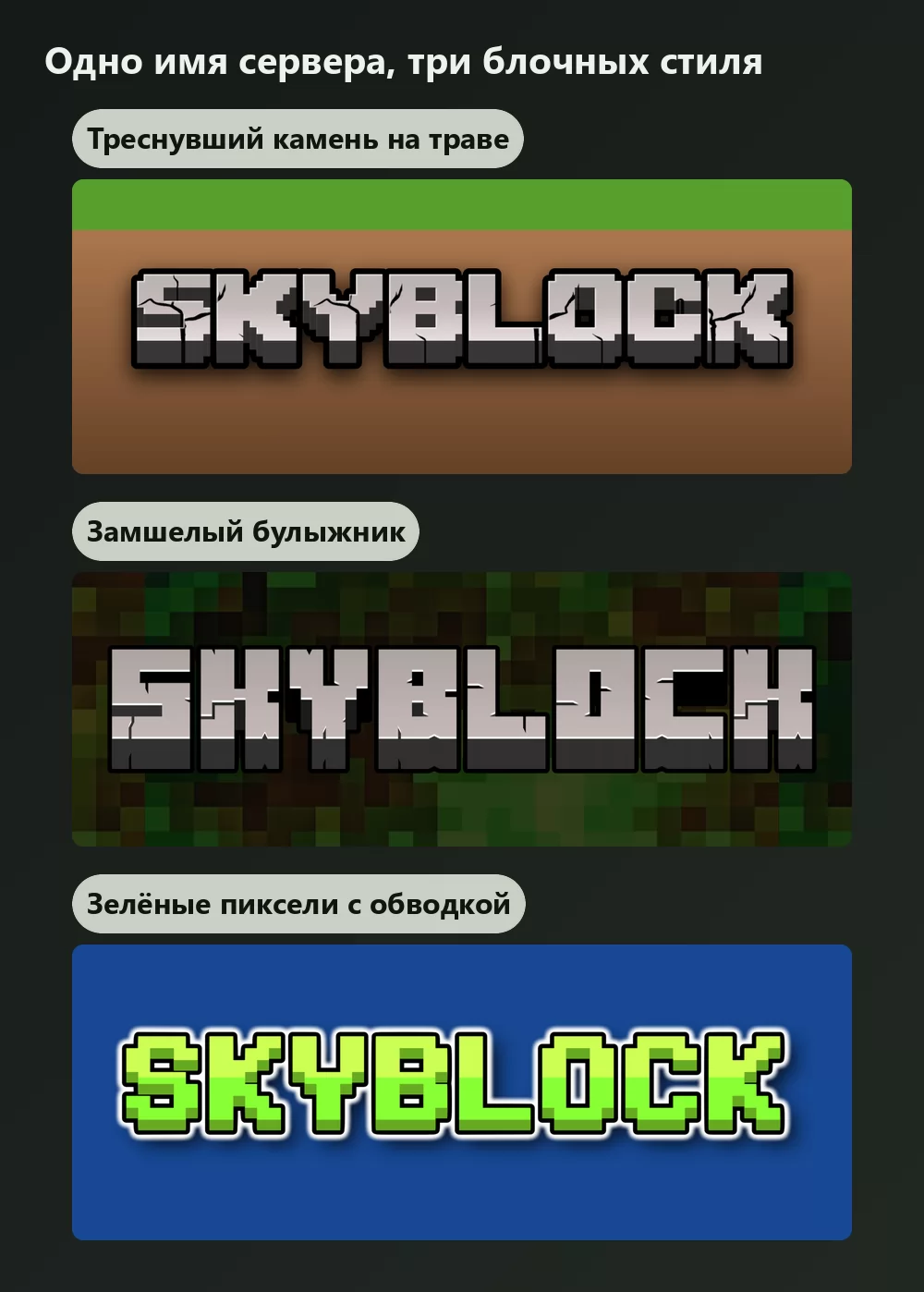
Наберите «шрифт Minecraft» в поисковике, и вы получите две группы результатов, которые противоречат друг другу. Одна предлагает плоский пиксельный шрифт. Другая предлагает толстые каменные буквы с трещинами. И те и другие называют себя шрифтом Minecraft.
Правы обе, потому что Minecraft использует два совершенно разных шрифта, а игра поставляет только один из них. Почти все, кто ищет, представляют себе второй.
Короткий ответ: это два шрифта, а не один
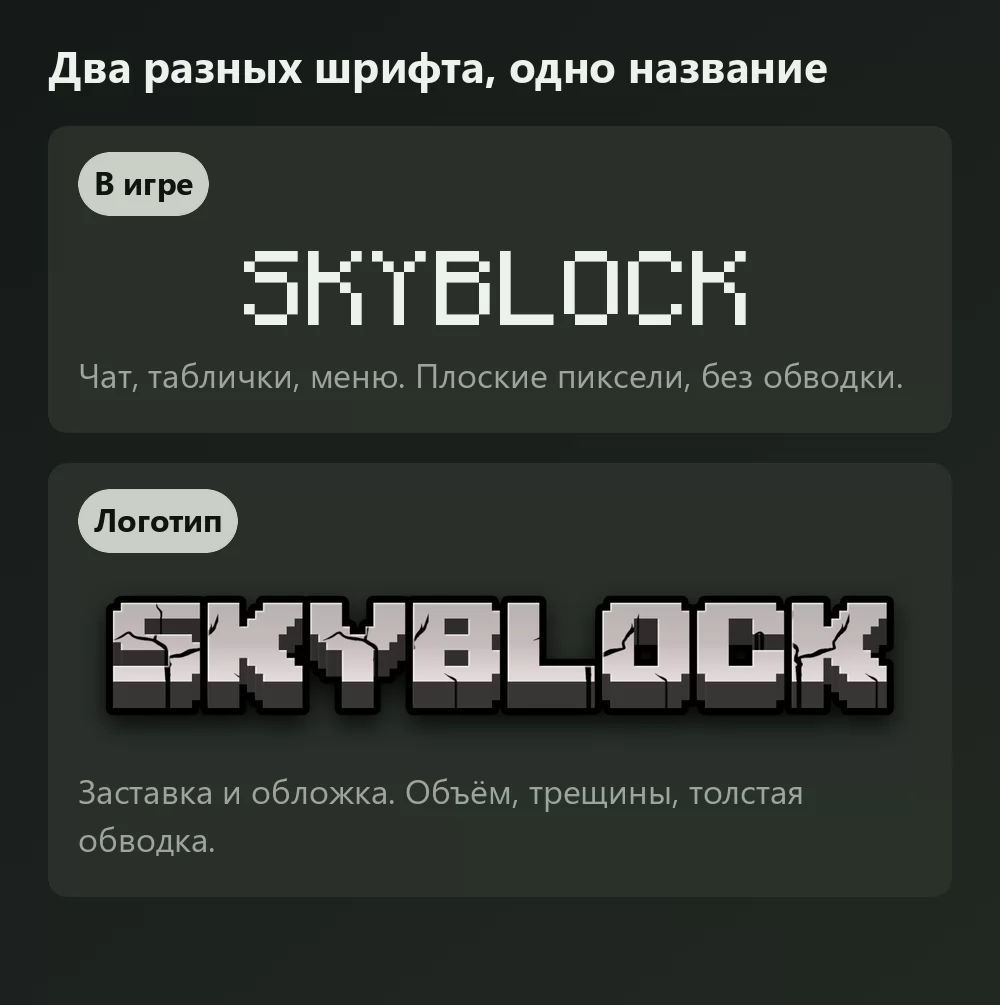
Mojangles это тот, на котором работает игра. Мелкий пиксельный шрифт чата, названий предметов, табличек, меню и всех тех табло, которые вы разглядывали, прищурившись. Плоский, без объёма, без обводки.
Шрифт логотипа это толстые буквы, высеченные в камне, с заставки и с обложки. У него есть глубина, тяжёлая тёмная обводка и трещины, проходящие сквозь буквы. В игре его вообще нет как шрифта: это рисунок.
Если вы делаете баннер сервера, обложку для YouTube, логотип SMP или шапку Discord, вам нужен второй. Если вы воссоздаёте сообщение в чате или табличку, вам нужен первый.
Откуда на самом деле взялся Mojangles
Это по-настоящему хорошая деталь, и большинство страниц её перевирает.
Mojangles старше самого Minecraft. Маркус Перссон нарисовал его в 2001 году для своей более ранней игры Legend of the Chambered, за восемь лет до появления Minecraft, и взял за основу пиксельный шрифт 8 x 8, встроенный в видеокарту IBM EGA 1984 года. Шрифт, который вы связываете с самой продаваемой игрой в истории, начинал жизнь как аппаратный набор символов ранних графических плат для ПК.
Заодно одно исправление, потому что везде пишут обратное: Mojangles не моноширинный. Его глифы нарисованы по сетке в 8 пикселей, но ширина меняется от 1 до 8 пикселей, поэтому заглавная M занимает намного больше места, чем строчная i. Несколько популярных руководств утверждают противоположное. Запустите любой мир Minecraft и посмотрите на табличку: проверка займёт две секунды.
Monocraft, у которого чистая лицензия
Он же и самый полный из всех: более 1500 глифов, охватывающих латиницу с диакритикой, кириллицу и греческий, плюс стандартный галактический алфавит со стола зачарования. Поставляется в форматах .ttf и .ttc, и автор прямо указывает, что это фанатский проект без единого ресурса Mojang.
Два момента. Он намеренно моноширинный, в отличие от Mojangles, потому что задумывался как шрифт для программирования: длинные слова выглядят чуть шире, чем в игре. И у него нет китайских, японских и корейских глифов, что важно, если вы собирались набирать им текст CJK.
Бесплатные пиксельные реконструкции
Самая скачиваемая называется просто «Minecraft», автор Craftron Gaming, и на DaFont она приближается к пяти миллионам загрузок. Это файл TrueType размером 6 КБ, воспроизводящий плоский вид из игры, и DaFont объявляет его на 100 % бесплатным.
Стоит проявить осторожность: DaFont относит его к разделу «Public domain / GPL / OFL», а это три разные лицензии с тремя разными наборами обязательств. Если проект клиентский или вообще коммерческий, прочитайте файл, идущий вместе с загрузкой, а не доверяйте названию категории.
MineCrafter, тот самый шрифт логотипа, и лицензия, которую все пропускают
MineCrafter от Madpixel Designs это надпись из высеченного камня с логотипа, с вариантом с трещинами. Его скачали около 4,75 миллиона раз, и именно его большинство в итоге и устанавливает, потому что это тот вид, который они себе представляли.